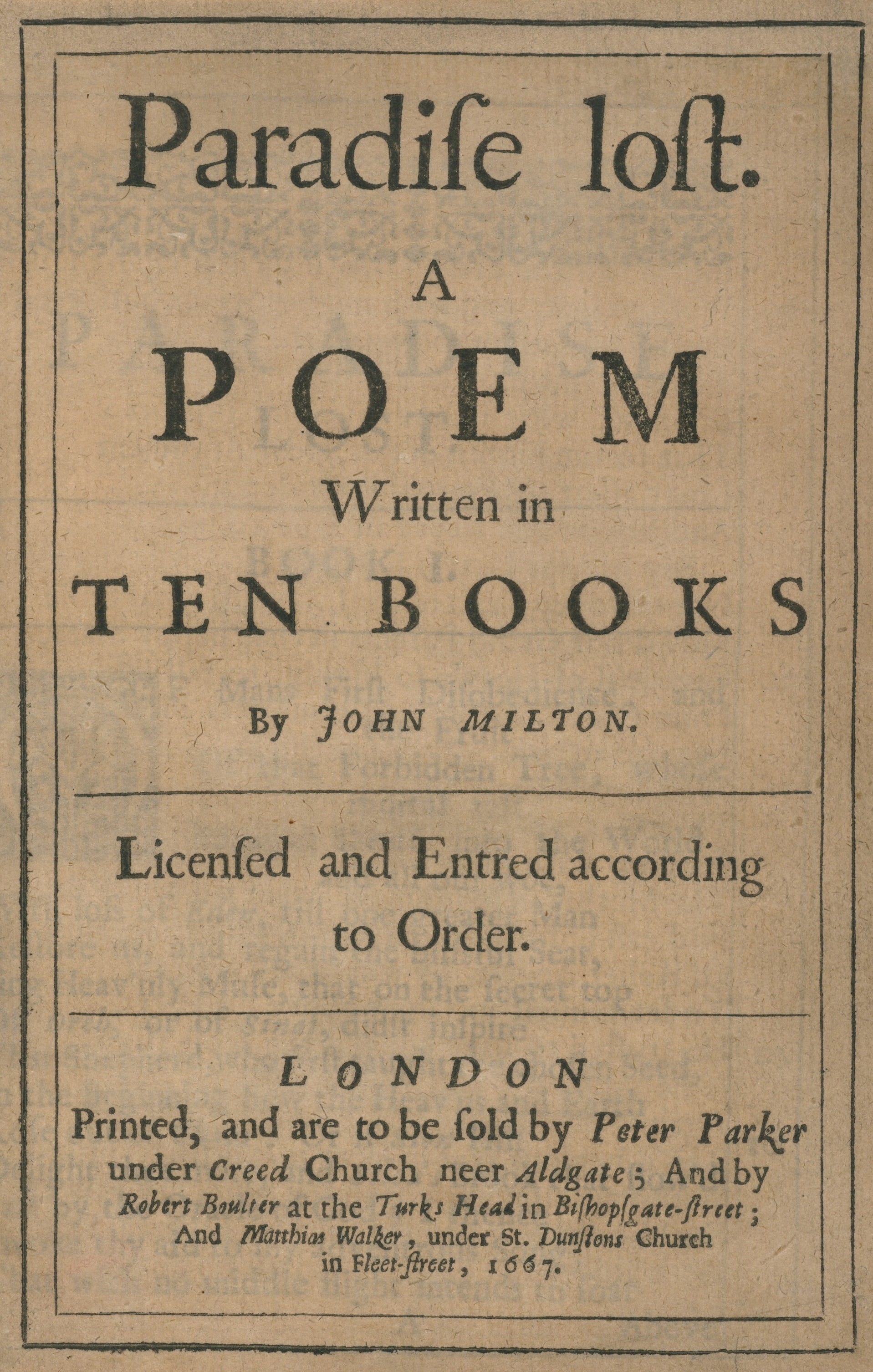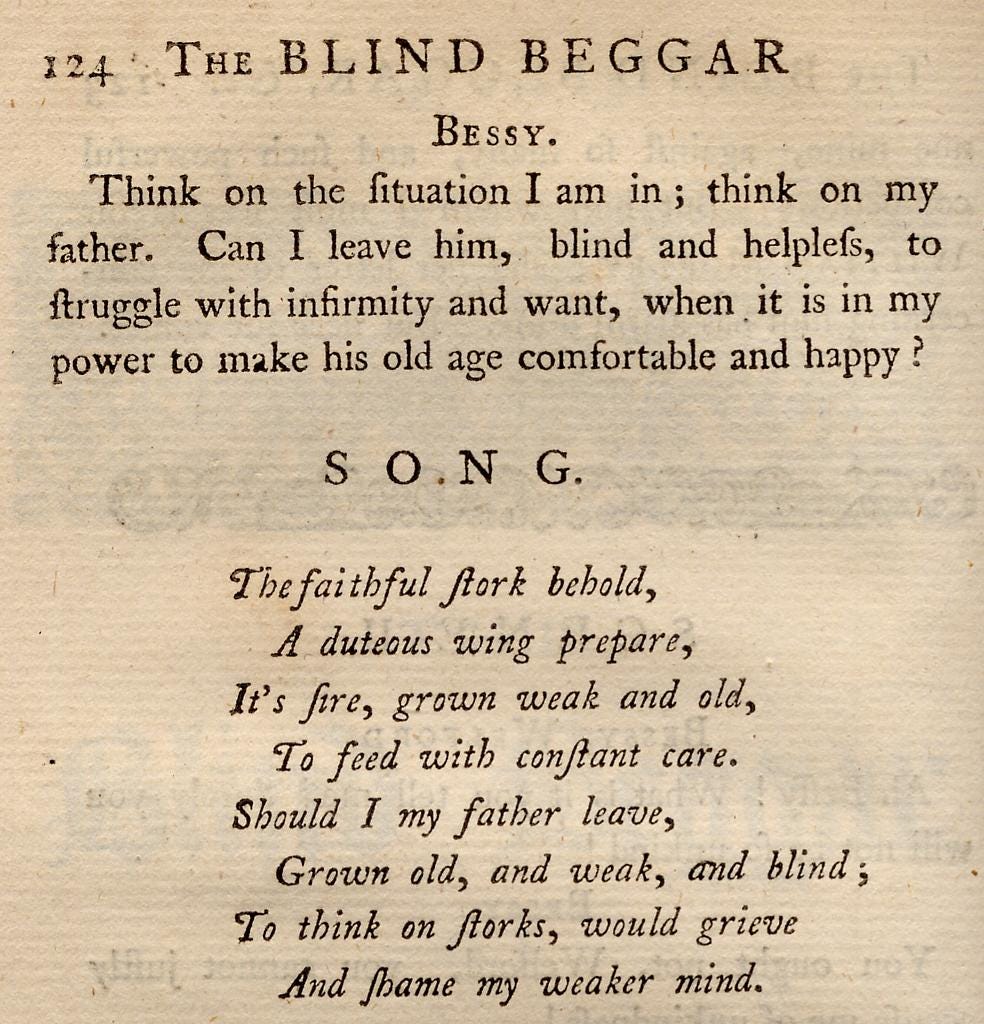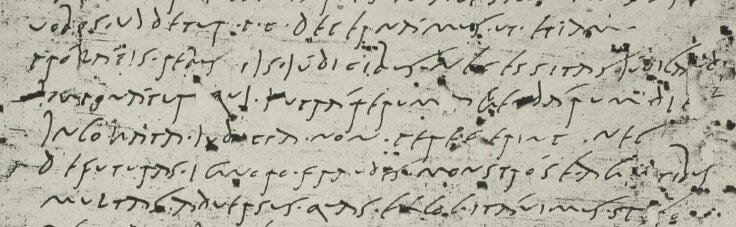
Tipo Aquilo #29 – O “s” longo está morto, viva o “s” longo
O congreſſo da ſociedade de deguſtadores das ſalſichas ſuecas, em inuſual conſenſo, recuſou com ſatisfação a ſubſtancial propoſta de ſaborear guloſeimas eſcandinavas a cuſtos inſignificantes ſob a circunſtância nefaſta de manifeſtar ſolenemente sua eſcolha propenſa aos petiſcos noruegueſes.
O abandono do “s” longo foi daquelas raras vezes na história em que linguistas e tipógrafos concordaram que, ao invés de lidar com várias regras e exceções sobre o uso de duas formas da mesma letra, é mais prático lidar apenas com uma. Houve outras vezes em que a indústria tipográfica ajudou a moldar a ortografia, mas por ora, vamos para a história dessa forma antiga do “s”.
Embora a letra “s” tenha origem fenícia, a forma que ela tem hoje vem das letras usadas no império romano. Enquanto o “s” curto e o “S” vêm das letras imperiais, utilizadas em monumentos gravados em pedra, o “ſ” vem das letras cursivas, utilizadas no dia-a-dia e até em alguns documentos oficiais. Ler documentos escritos em cursivo romano é uma atividade restrita à paleografia, mas algumas letras já tinham aparência semelhante às letras romanas atuais.
A letra “s” tinha aparência semelhante à letra grega gamma (“γ”), feita com um movimento que começava na altura das letras comuns, fazia uma volta na linha de base, e subia novamente até uma altura superior à das outras letras. Por isso, a representação do “ſ” parece um “f” com a barra cortada; na verdade, a barra cortada é o início da escrita do “s” longo, em que o lápis desce até a linha de base no sentido vertical, e depois sobe pelo mesmo caminho até a altura das ascendentes.
O “ſ” foi usado até o séc. XIX; por isso, quase todas as escritas contemplavam o “s” e o “ſ”, assim como as primeiras fontes tipográficas tinham tipos para as duas formas. Cada língua tinha sua forma de lidar com essa ambiguidade, embora algumas línguas eslavas tratassem-nas como letras diferentes. Em línguas latinas, era comum que o uso do “s” fosse restrito à ultima letra de cada palavra, e as demais fossem “ſ”; de certa forma, a letra sigma do alfabeto grego funciona de forma análoga, tendo uma forma intermediária (“σ”) e uma forma final (“ς”).
No entanto, o “ſ” já não é mais usado em textos comuns em nenhum idioma há muito tempo, e a morte dele geralmente é creditada a dois grandes nomes da história da tipografia: François-Ambroise Didot e John Bell. O primeiro, francês e pai de Firmin Didot, decidiu não gravar mais tipos para o “s” longo em 1781, encorajando outras fundições a seguirem o mesmo caminho. O segundo, inglês, encomendou à fundição de William Caslon uma fonte tipográfica sem o “s” longo em 1788, utilizando-a em seu jornal e demais publicações. Ambos deram força a uma tendência vista pela primeira vez na Espanha, em um volume impresso por Gabriel Ramirez em 1761, e seguido por Joaquín Ibarra dois anos depois.
Após o início do séc. XIX, o uso do “s” longo foi progressivamente encerrado. Nos Estados Unidos, o uso mais famoso do “ſ” está na United States Bill of Rights de 1789, grafando o primeiro “s” de Congress; apesar disso, o país recém-independente foi um dos primeiros a abandonar o “s” longo. Um exemplo desse abandono repentino está na Guerra Anglo-Americana de 1812, em que o documento de declaração de guerra das ex-colônias usa apenas o “s” curto, e a resposta britânica ainda utiliza o “ſ”. Contudo, novas fontes eram vendidas apenas com o “s” curto, e os poucos volumes ainda impressos com o “ſ” até o fim do século vinham de gráficas antigas.
Dessa forma, o “s” sinuoso estabeleceu-se como a única contraparte para o “S” maiúsculo. Alguns resquícios do “s” longo ainda existem, como a letra eszett (“ß”), comum no idioma alemão; o símbolo de operação matemática de integral (“∫”); e o caracter esh (“ʃ”), usado no alfabeto fonético internacional, que representa o som fricativo que faz em vogais nas palavras chave, queixa ou coxixo. Algumas línguas que usavam o “ſ” como uma letra distinta do “s” substituíram-na por um “s” curto com diacrítico. No fim das contas, para o bem da simplicidade, o “ſ” ficou para a paleografia e o “s” para o nosso uso cotidiano. Assim como o “g” caligráfico, o “s” é uma das letras mais odiadas difíceis de trabalhar para designers de tipos, mas isso é assunto pra outra edição e eles que lutem. ;)
Recomendações:
🎧 Podcast: IconicCAST #102 – Desenhando Letras, com Henrique Lira, Aline Kaori, Gui Menga, Isabella Lião e Lygia Pires conversando sobre a atividade e ensino de lettering e caligrafia.
🎥 Vídeo: Exploring the 18th Century: the Long “S”, que conta sobre a história do uso e abandono do “s” longo no séc. XVIII.
🔗 Link: Quirks of Old Documents: Spelling, Tildes, Ampersands, and the Long S, um apanhado de recursos caligráficos e tipográficos utilizados em documentos antigos.